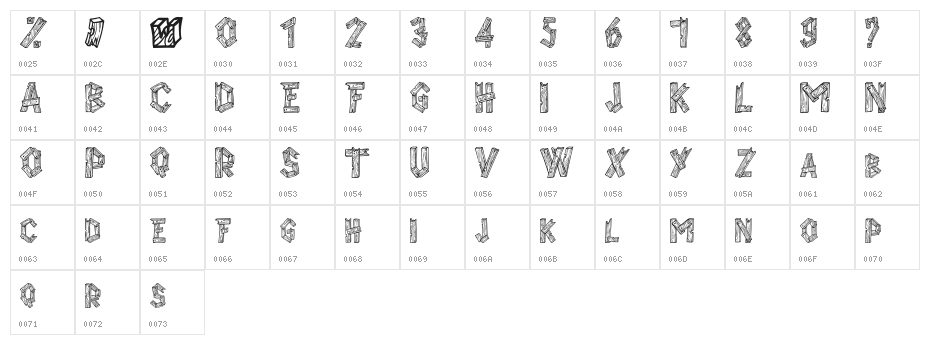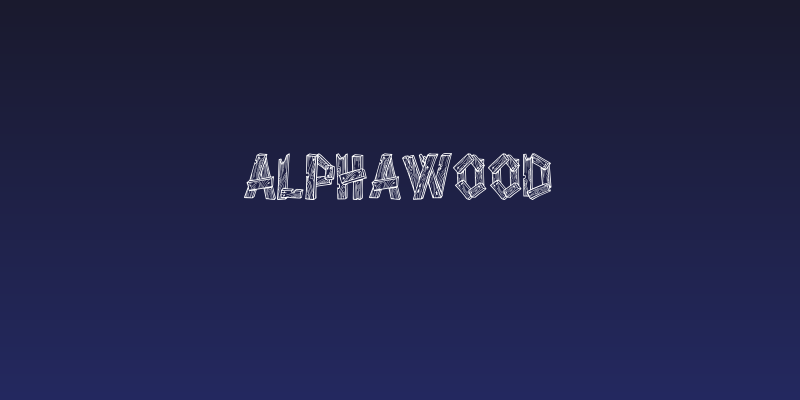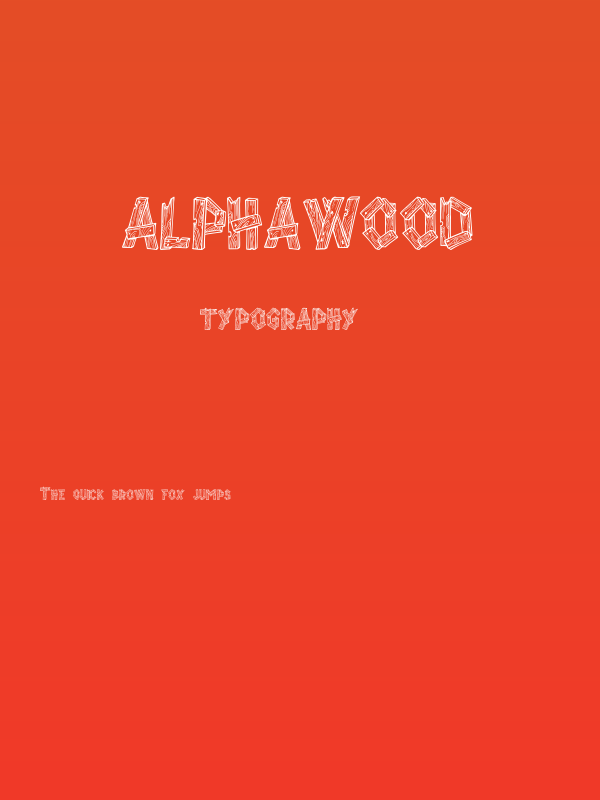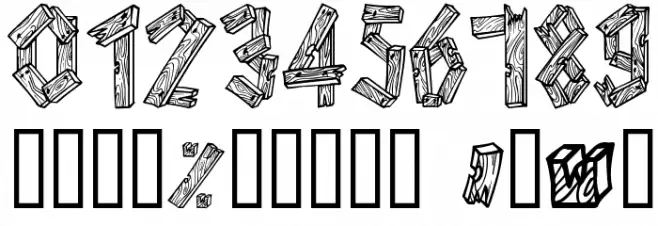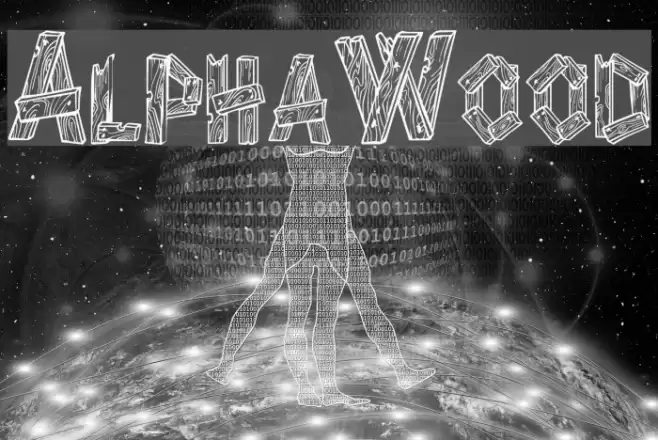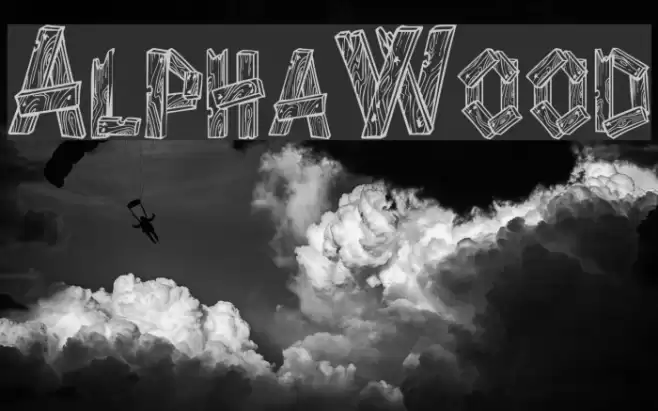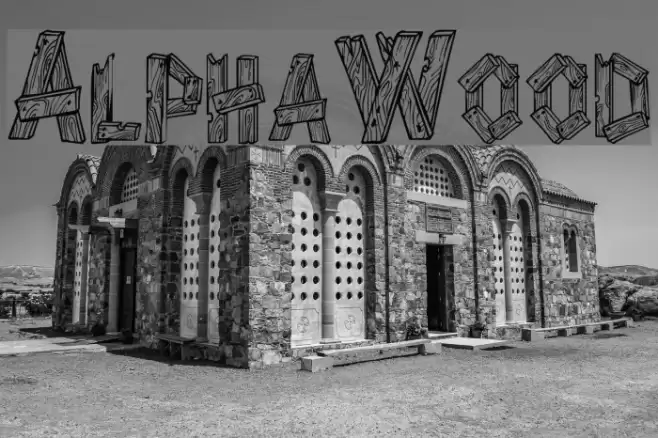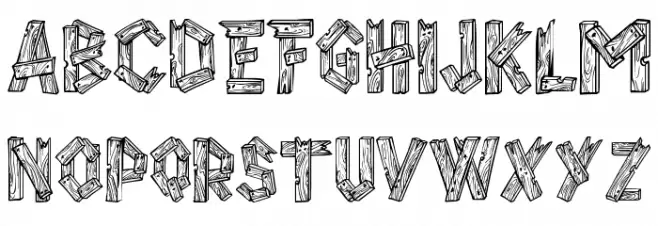
AlphaWood Font
| Stil general | Rustic, Organic, Natural |
| Proiecte propuse | Ideal for nature-themed posters, eco-friendly brand logos, outdoor event invitations, and rustic signage. |